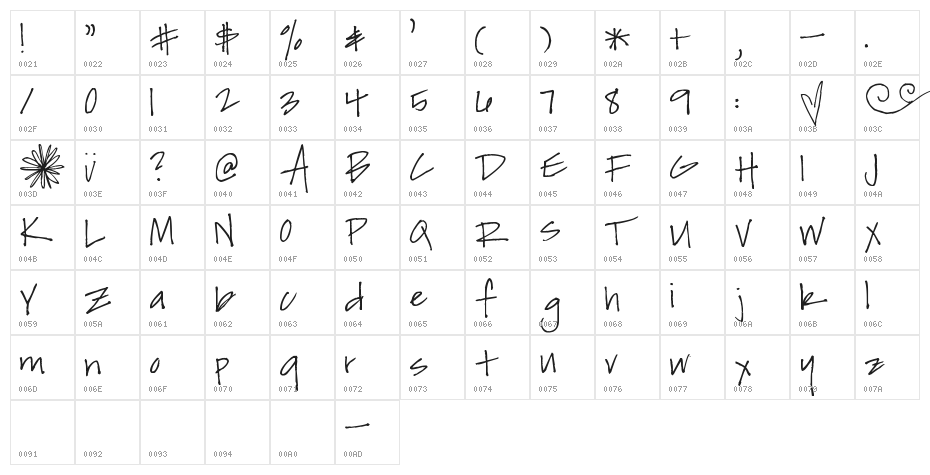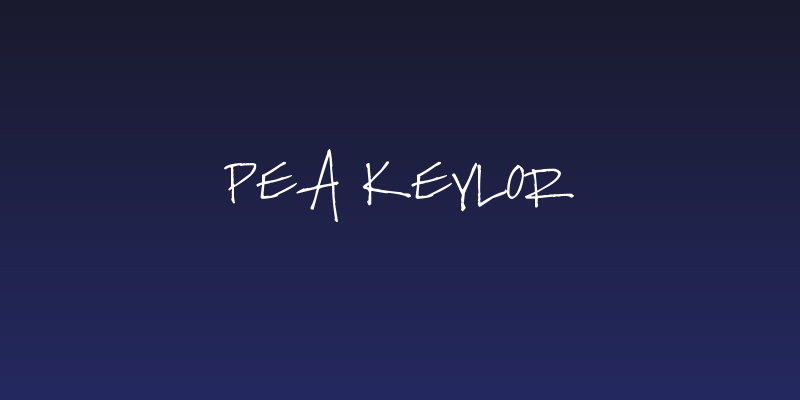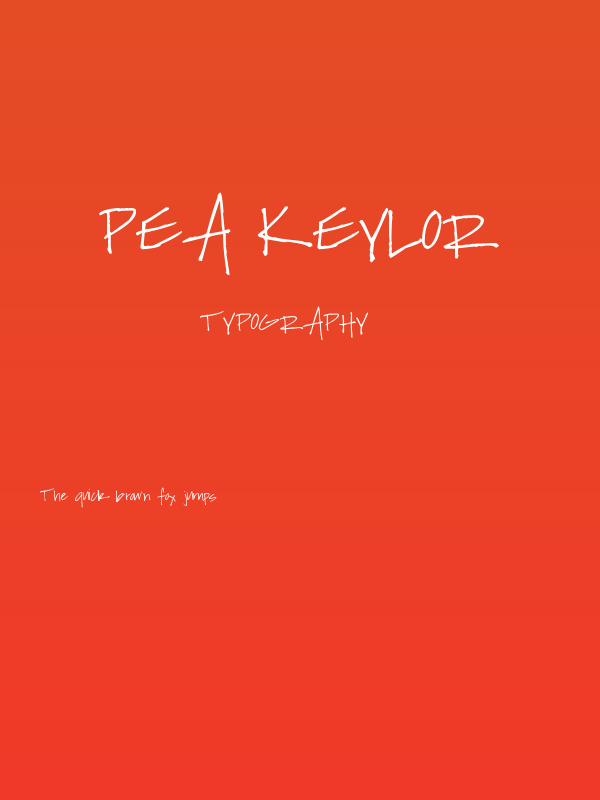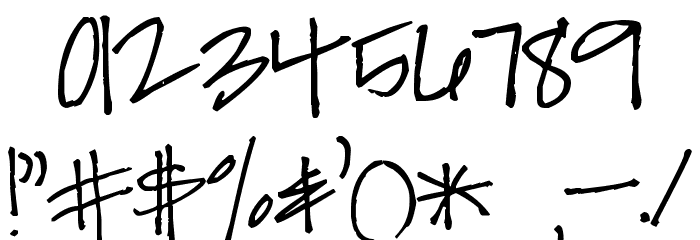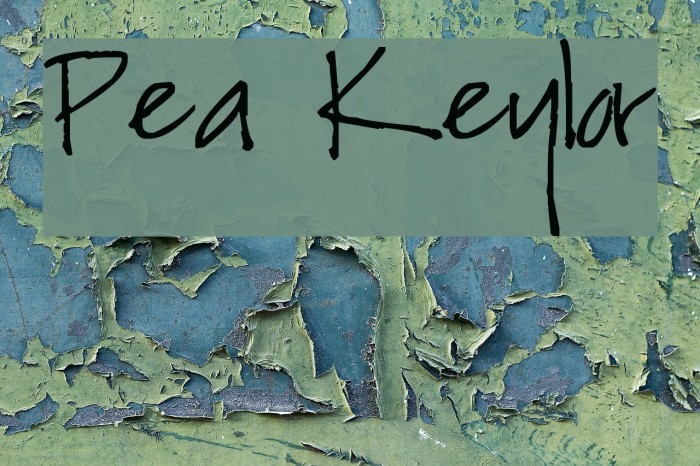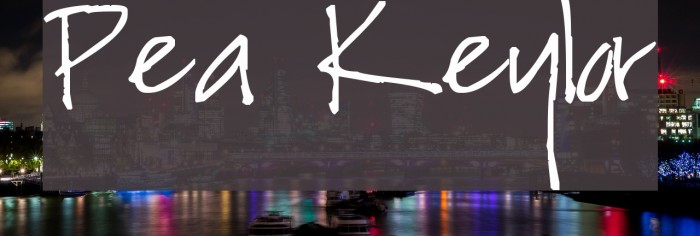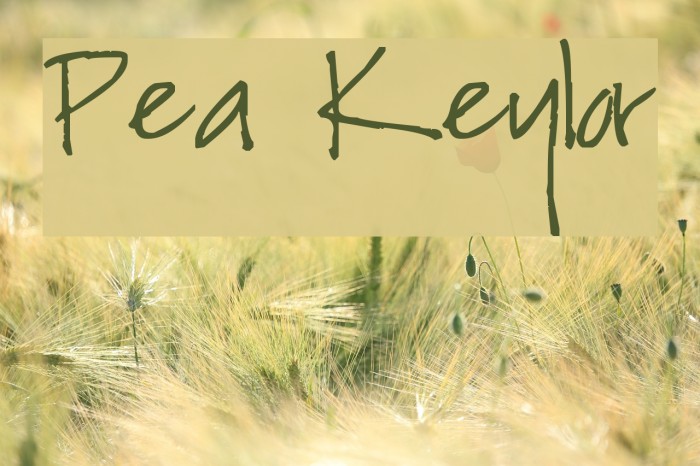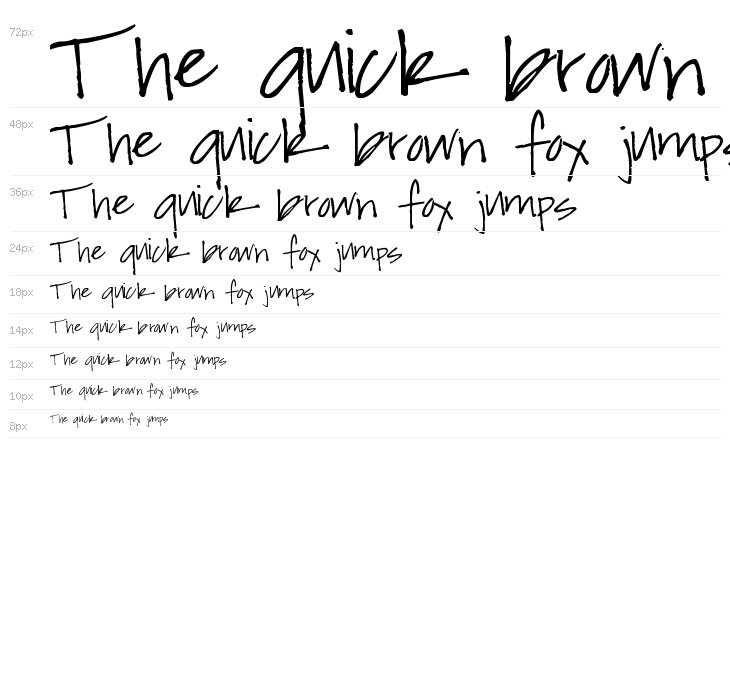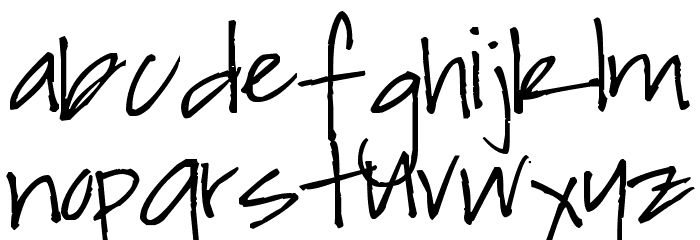
Pea Keylor Font
| Nome | Pea Keylor |
| Stile generale | Casual, Playful |
| Caso d'uso | Headlines, Informal text, Creative projects |
| Progetti proposti | Ideal for greeting cards, personal blogs, creative posters, and informal branding. |